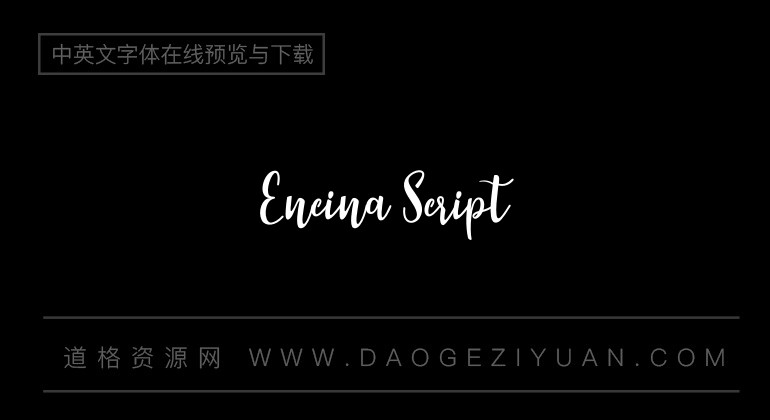
Encina Script
Encina Script 是一种优雅、手写风格的字体,适合用于印刷品、包装、广告、品牌标识、手写信件等设计领域。这种字体的特点在于其流畅的曲线和连笔,使得文字具有艺术感和自然感。 Encina Script 字体包含了多种字重和变体,可以满足不同场景下的需求。此外,Encina Script 字体还支持多种语言,包括英语、法语、西班牙语、德语、意大利语等,适合全球化品牌的设计。
Encina Script是一款非常不错的手写艺术字体,具有很好的视觉感,适合于文化类的宣传设计、商业类品牌的广告和产品包装设计以及个性化文字排版等较多场景。